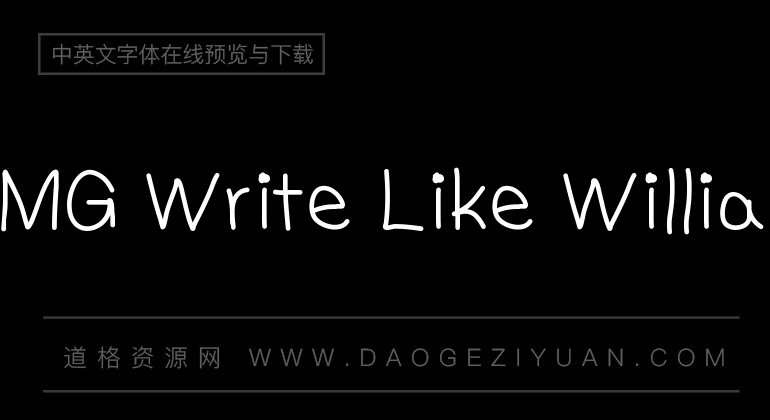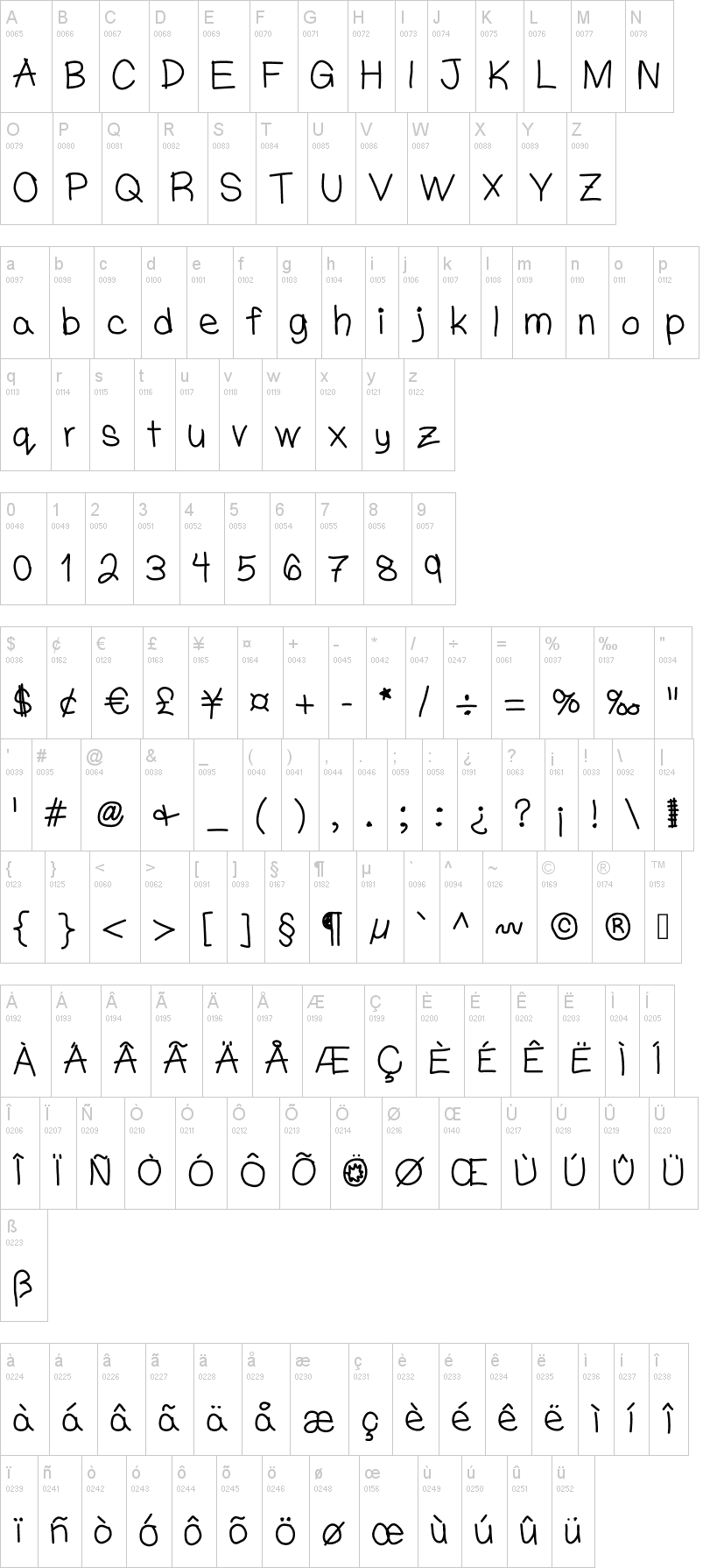
? OMG Write Like William 字体是一款手写风格的英文字体,它是由英国设计师 William Bayley Suckling 手写而成,拥有优雅、温柔、活泼的特点,可以用于宣传册、海报、活动邀请函等,是一款优雅、温馨的字体。内容介绍
OMG Write Like William是一款非常不错的手写艺术字体,具有很好的视觉感,适合于文化类的宣传设计、商业类品牌的广告和产品包装设计以及个性化文字排版等较多场景。